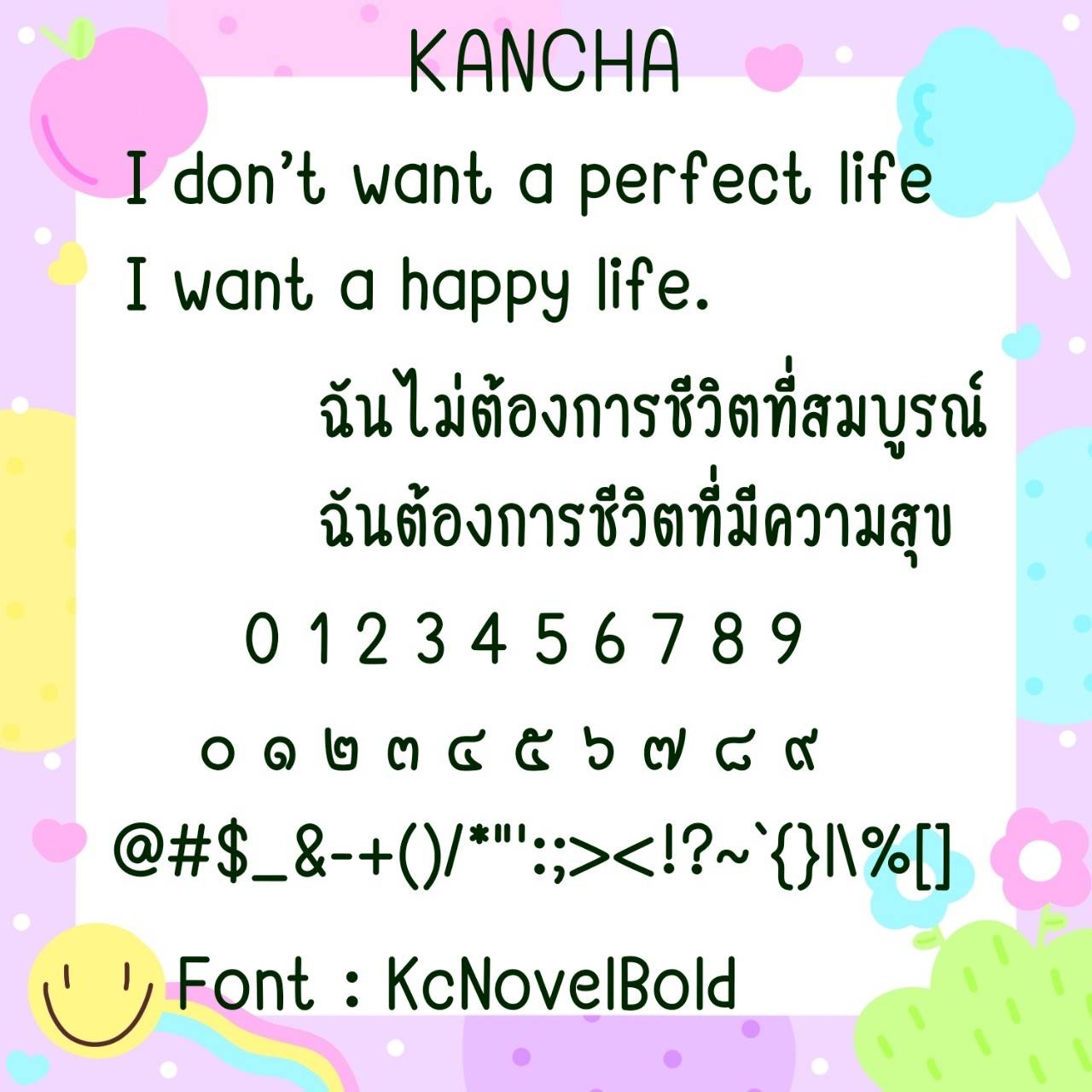
Font KcNovel
ชื่อสินค้า : Font KcNovel 💙
🔸ฟอนต์ไม่มีหัว ตัวผอม แต่อ่านง่าย ดูเป็นระเบียบนิดๆ เหมาะกับการใช้งานหลากหลาย แถมยังมีตัวพรีเมียมเก๋ๆให้ในชุดอีกด้วยค่ะ🥰💙
🔹The font has no head, is thin, but is easy to read and looks a bit organized. suitable for a variety of applications There is also a cool premium item in the set as well.🥰💙